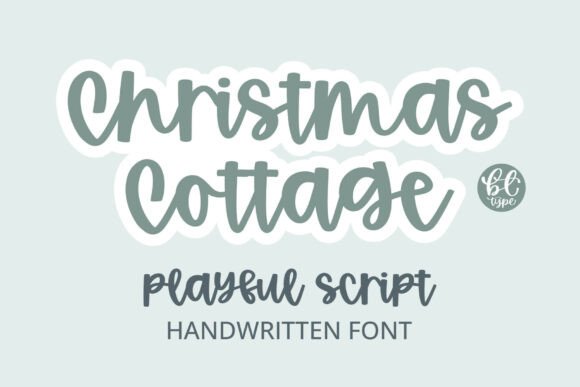
Christmas Cottage
適切なデザイン要素を見つけるのは難しい場合がありますが、Christmas Cottageは作品を即座に引き立てる優れたコレクションを提供します。
POD(オンデマンド印刷)製品、結婚式の招待状、またはソーシャルメディアのグラフィックを作成している場合でも、Christmas Cottageは理想的です。